Schnörkelschrift: Verspielte Fonts von Type-Designern
Mit Schnörkelschrift lassen sich kreative und individuelle Designs umsetzen. Diese Schriften beeindrucken durch ihre verspielten Schwünge, dekorativen Elemente und elegante Typografie. Hier finden sich kostenlose Schnörkelschriften zum Herunterladen.
Schnörkelschrift bezeichnet Schriftarten, die sich durch geschwungene Linien, verzierte Buchstaben und oft handschriftliche Details auszeichnen. Diese verschnörkelten Schriften eignen sich besonders für besondere Anlässe wie Hochzeiten, Einladungen oder Grußkarten. Häufig basieren sie auf Kalligraphie- oder Handschriftenstilen und bieten Opentype-Features wie alternative Zeichen, Ligaturen und Schmuckbuchstaben.
Typische Einsatzbereiche für Schnörkelschriften sind romantische Designs, luxuriöse Verpackungen oder Projekte, bei denen Eleganz und Persönlichkeit im Vordergrund stehen. Diese Sammlung stellt einige der schönsten Schnörkelschriften vor, die kostenlos heruntergeladen und teilweise auch kommerziell genutzt werden können.
Beispiele für Schnörkelschrift
Welldone
Die kalligraphische Schnörkelschrift „Welldone“ kombiniert florale Elemente mit verspielten Schwüngen. Perfekt für Designs mit romantischem Flair.
Le Grand Amour
Diese elegante Schnörkelschrift eignet sich hervorragend für Hochzeiten. Ihre geschwungenen Buchstaben verleihen jedem Schriftzug einen edlen Touch.
Kintamani Script Font
Klassisch und elegant wirkt diese verschnörkelte Schrift von Ardyanatypes, die im handgeschriebenen Stil daherkommt. Sie eignet sich beispielsweise für Hochzeitsdesigns, Verlobungseinladungen, flirtende Visitenkarten, Logos, Fotoillustrationen und Projekte, die von einer handschriftlichen Note profitieren.
Brigitta
Die Schnörkelschrift wartet mit schwungvollen Herzen auf. Der Font im handgeschriebenen Stil enthält zudem weitere alternative Zeichen, Ligaturen und mehr. Eine kostenlose Demo-Version kann für private Zwecke heruntergeladen werden.
Maligai Script Font
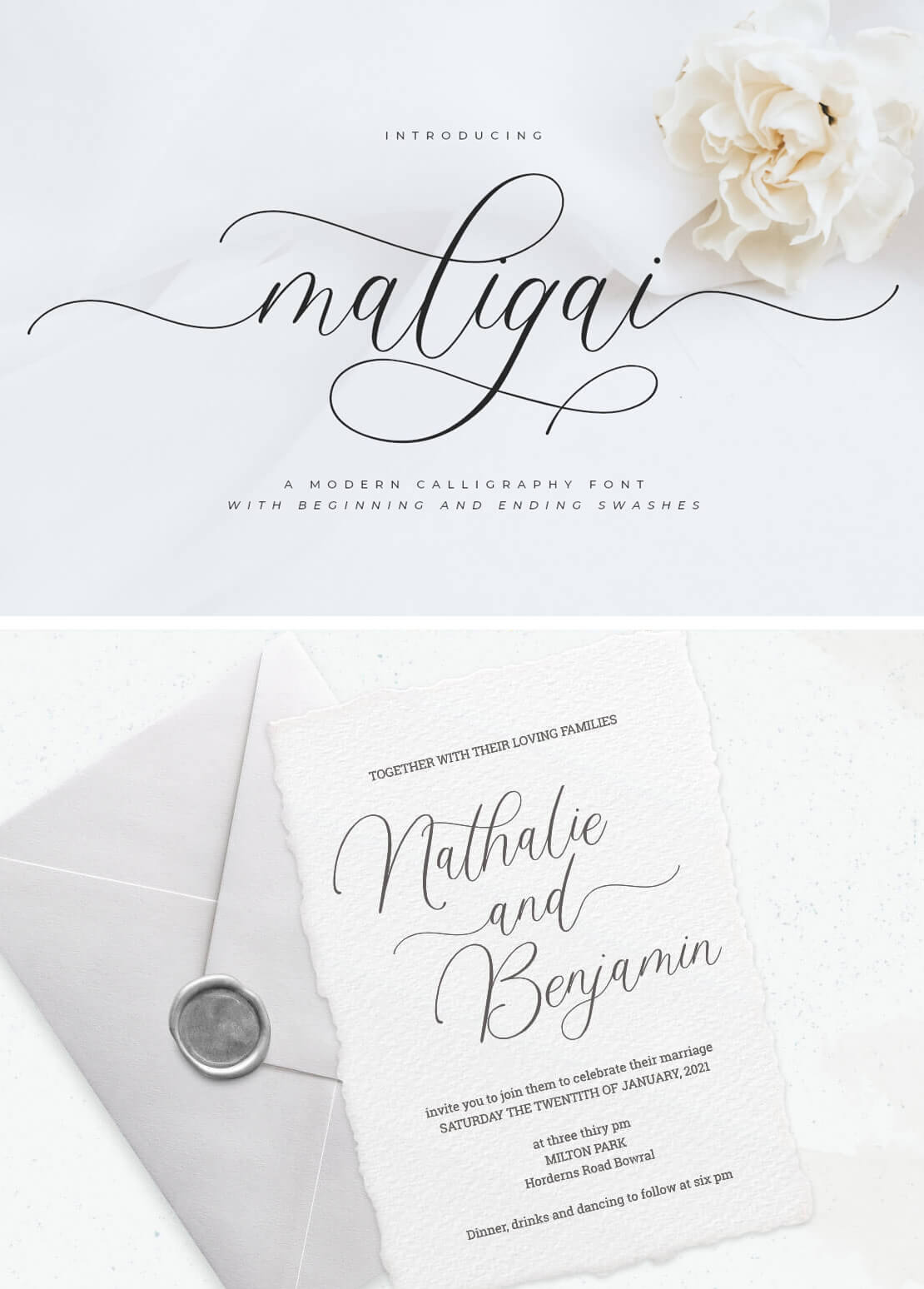
»Maligai« ist eine elegante Schriftart, die durch entsprechende Sonderzeichen und alternativen Glyphen ihre Wirkung entfaltet. Das prädestiniert sie beispielsweise für Hochzeiten, feminines Branding, Karten, Verpackungen und mehr. Eine Nutzung ist für private Zwecke kostenlos.
Art Maria
Ein moderner und verspielter Handschriften-Font, der zudem alternativen Zeichen und weitere Opentype-Features bietet. Enthalten sind neben Groß- und Kleinbuchstaben auch eine Auswahl an zusätzlichen Satzzeichen und Ligaturen. Den Demo-Font gibt es kostenlos zum Downloaden. Darüber hinaus findet man auf FontBundles die vollständige Version dieser Schnörkel-Schrift.
Ayulia Molga
Diese verschnörkelte Schriftart wurde von AuthenType gestaltet. Die klassisch und elegant zugleich wirkende Script-Schrift lässt sich für vielfältige Zwecke verwenden. Durch alternative Zeichen kommt Abwechslung in das Schriftbild. Wie der entsprechenden behance.net-Seite zu entnehmen ist, darf »Ayulia Molga« in privaten und kommerziellen Projekten verwendet werden.
Rabitta Calligraphy Font
Ein kalligraphischer Font, der an eine Handschrift erinnert und zudem noch mächtig verspielt daherkommt. Auffallend bei dieser Schnörkelschrift ist die wechselnde Strichstärke. Diese sorgt für einen individuellen Look. Die Nutzung von »Rabitta« ist im privaten Bereich kostenlos. Für eine kommerzielle Verwendung ist eine entsprechende Lizenz erforderlich.
Mirandany
Diese Schriftart im handgeschriebenen Stil wirkt verspielt und romantisch zugleich. Die Verwendung dieser Schriftart ist für private Zwecke kostenlos. Darüber hinaus kann separat eine Premium-Version für den kommerziellen Einsatz erworben werden.
Valencia Sweetness Duo Font
Wie von Hand mit einem Pinsel geschrieben wirkt diese Schriftart. Sie eignet sich beispielsweise für Hochzeitseinladungen, Dankeskarten, Grußkarten und überall dort, wo eine persönliche Note erforderlich ist. Enthalten sind neben Groß- und Kleinbuchstaben auch alternative Zeichen, die den handschriftlichen Charakter unterstreichen. Die Schnörkelschrift kann für private und kommerzielle Zwecke verwendet werden.
Galgadot
Elegant und luftig-leicht gibt sich »Galgadot«. Die verträumt wirkende Schnörkelschrift wurde von Luxusmode inspiriert. Enthalten sind 60 Ligaturen, verschiedene Striche und weitere schmückende Buchstaben. Die Demo-Version darf privat verwendet werden und gibt einen entsprechenden Einblick in die Schriftart. Mit der Vollversion stehen dann alle verschnörkelten Buchstaben zur Verfügung.
Antharis
»Antharis« ist ein eleganter Script-Font, der sich für vielfältige Zwecke verwenden lässt. Der Schnörkel-Font unterstützt mehrere Sprachen und enthält alternative Zeichen, die für den nötigen Schwung sorgen. Eine Verwendung ist im privaten Umfeld kostenlos. Für kommerzielle Projekte ist eine entsprechende Lizenz erforderlich, die sich bei FontBundles.net erwerben lässt.
Marmia
»Marmia« ist eine schwungvolle Schrift im handgeschriebenen Stil. Verspielt sind die alternativen Zeichen und Schwünge ausgefallen. Zum Ausprobieren gibt es einen kostenlosen Demo-Font, der für private Zwecke verwendet werden kann.
Restuner Script
Dieser Script-Font bietet insgesamt 538 Zeichen. Darunter findet man auch viele verspielte Sonderzeichen, mit denen sich diese Schnörkelschrift optisch bereichern lässt. Der kostenlos herunterladbare Font kommt mit einer Premium-Lizenz und darf demnach privat und kommerziell gleichermaßen genutzt werden.